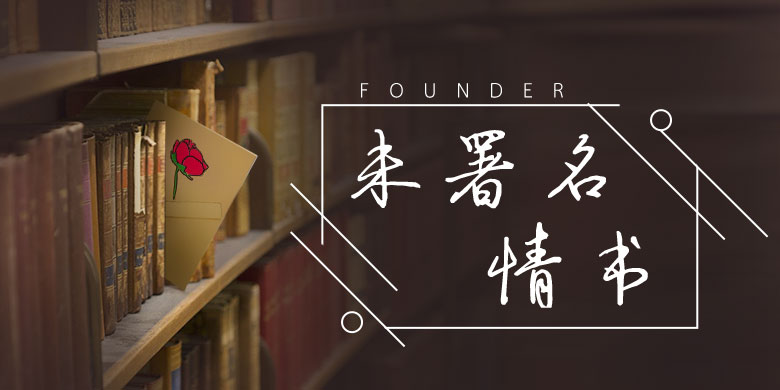
方正手迹-未署名情书
方正手迹-未署名情书,这款字体结构工整、笔画清晰,兼顾美观与易读性,适用于标题、正文、海报、包装、LOGO 等多种场景。字形优雅稳定,风格百搭耐看,适配日常排版与创意设计,让文字呈现更舒适、更具质感。方正手迹-未署名情书一笔一画,皆是细节,以均衡的比例、流畅的线条打造舒适视觉体验,字形端正大气,风格简约现代。无论是商业设计、品牌宣传还是日常排版,都能轻松驾驭,让文字更有格调与力量。方正手迹-未署名情书字体下载。
现代人用键盘多过用笔,很少能写上几个字,能写出有传统书法味的字,更是难能可贵,这款手写字体很好保留了传统行书的特点。适用于文艺类的书刊、品牌广告和产品包装设计,以及社交网络的个性化用字。